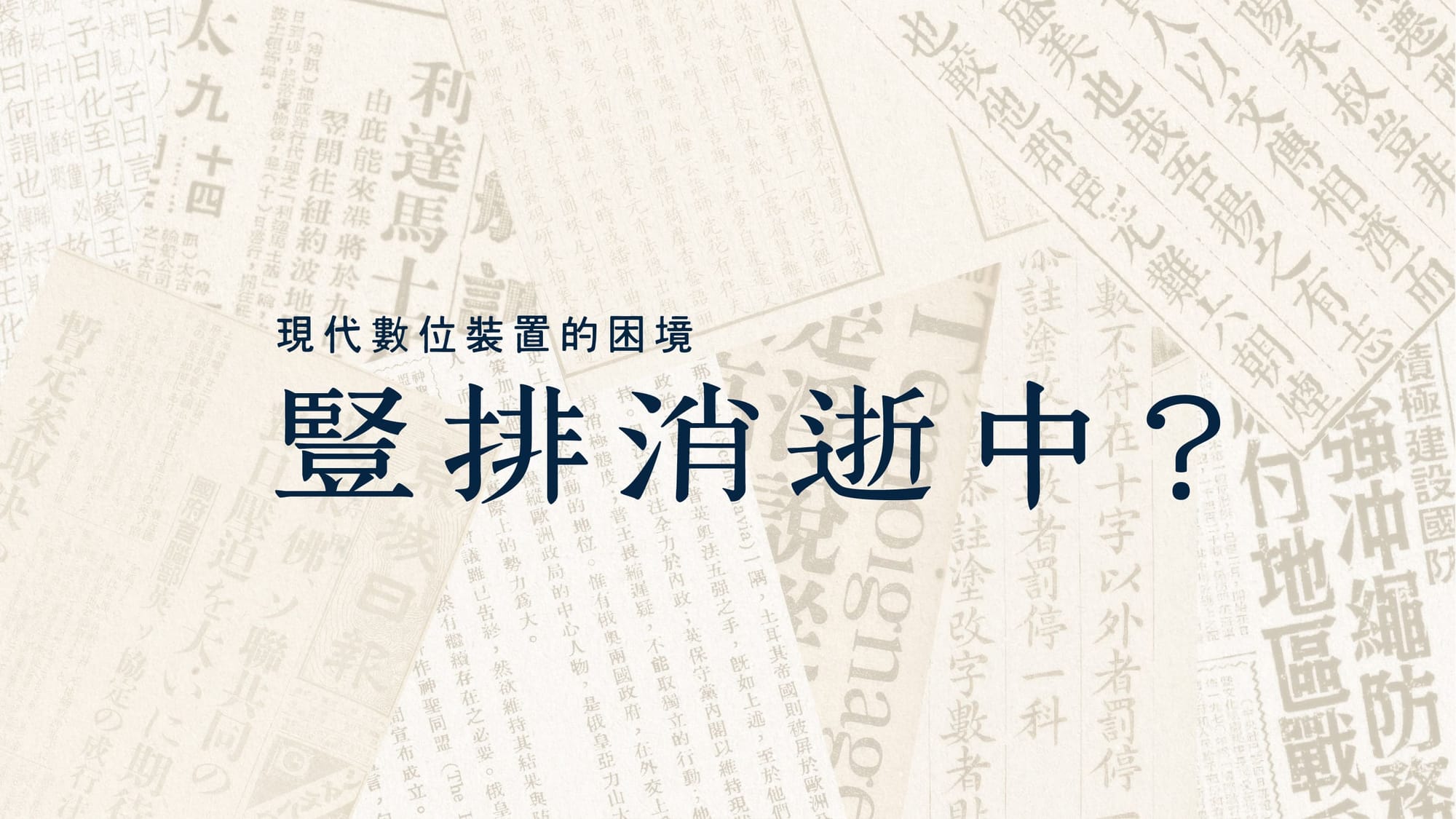
豎排消失中?現代數位裝置的困境
傳統的漢字書寫方向一直以來大多採用垂直形式。從以前的書法、刻本,再到現代的照排、鉛字,都多以這種形式與大家見面。
豎排/縱書
傳統的漢字書寫方向一直以來大多採用垂直形式。從以前的書法、刻本,再到現代的照排、鉛字,都多以這種形式與大家見面!
不過,這一切在進入數位時代後,開始發生變化,豎排開始漸漸消失,取而代之的是橫排文字,從電子文書到社群軟體絕大多,皆已改為橫式。
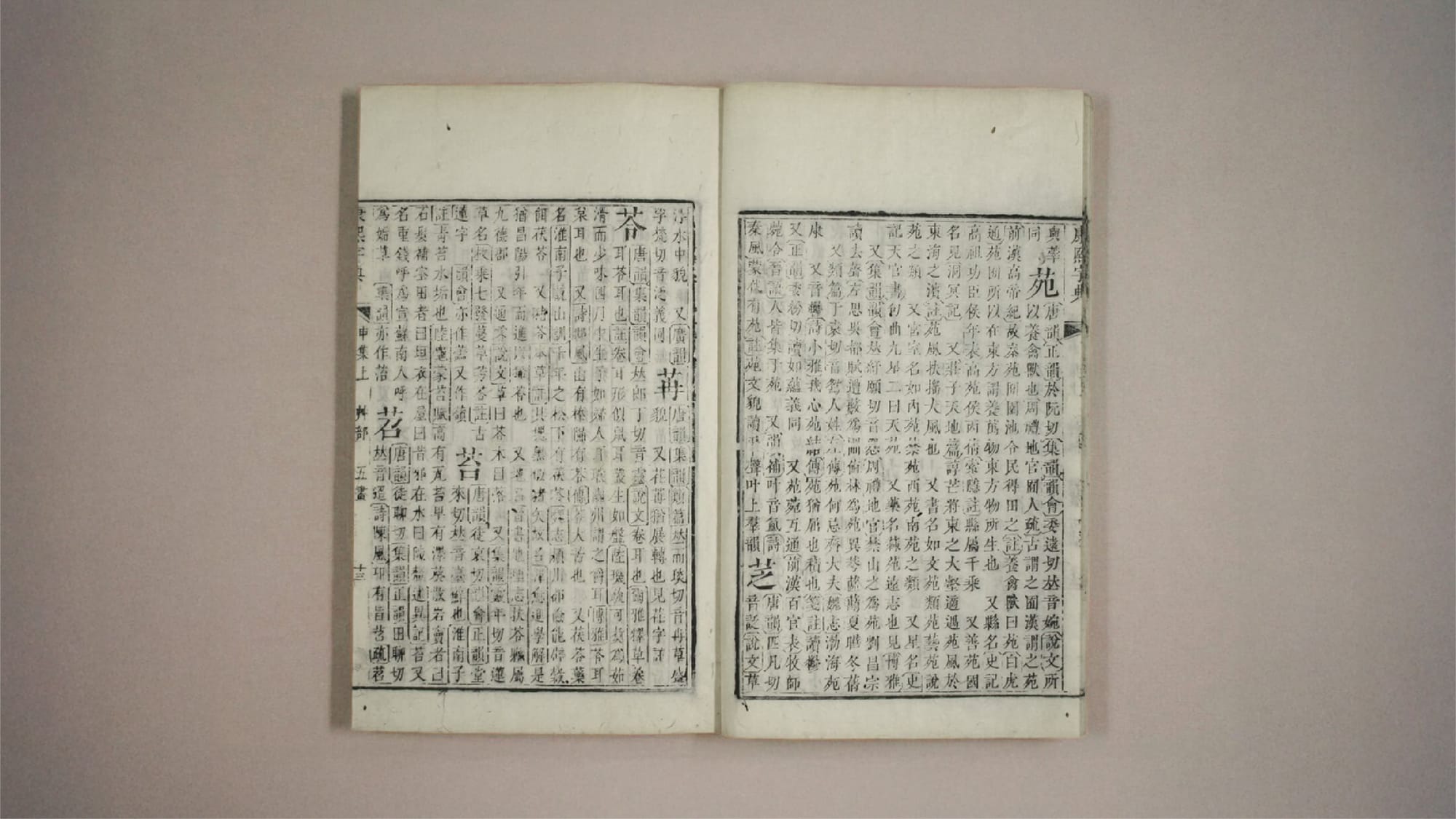
來自技術的侷限。
這一切的濫觴要從1973說起,當時美國Xerox公司,推出了Xerox Alto,這是世界上最早成熟的圖形化作業系統(是的,最早的GUI操作系統不是Microsoft、IBM或Apple推出的)。
再往前推的貝爾實驗、AT&T,甚至回朔到艾倫·圖靈......等人,這些公司、研究者絕大多數都來自歐美,或在歐美國家進行開發,所以他們用自己熟悉的語言開發在合理不過。
從技術層面來說,英文的組成也比中文等語系少得多,透過少數的字母符號組合不同結果,這在當時記憶體珍貴的硬體條件下,是最經濟的考量。
基於這樣的原因,自然的就會以拉丁為優先,或具體來說,是優先支援ASCII編碼的文字、習慣,而這些文種的書寫系統本生就是以橫排為主的。造就了現在以橫排
也沒這麼絕望?
講到電子裝置上的豎排,其實「電子書」就是最佳案例,目前主流的電子書裝置,大多可支援豎排模式。不是說逐漸消失嗎?
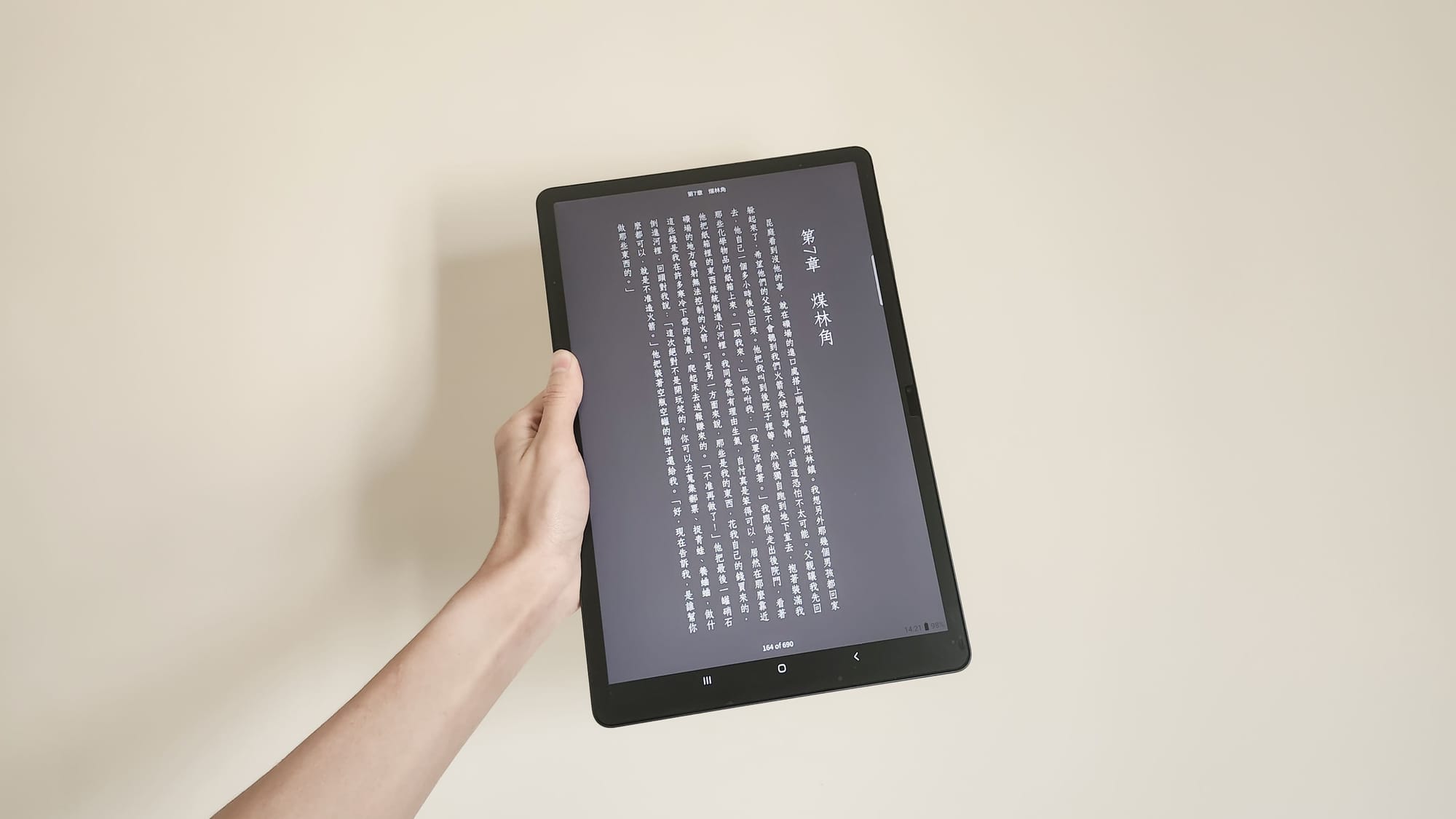
要回答這問題,要先掉書袋一下,如果你是電子書讀者,可能聽過電子書是使用 epub 格式,這種格式其實底層就是網頁技術,基於HTML 與 CSS,再加入配置文件等封裝成以.zip為編碼的文件。
既然是基於HTML 與 CSS,那當然是用瀏覽器解析囉!大多數的電子書軟體在你閱讀文章時,都會透過內嵌的小瀏覽器(通常是以Chromium為主,因為原生移動端Webview可能存在CSS兼容、效能等問題),進行解析。
沒錯!瀏覽器是支援的!這最早是在大約在2010年底時,由日本的專家學者提出相關草案,後被負責維護CSS的W3C組織正式支援。(這之中要感謝W3C團隊與特邀專家,這是個長故事,未來有機會也能在分享)。
瀏覽器是種選擇,但不是唯一。
只有瀏覽器支援豎排遠遠不夠。因為WebAPI的崛起,瀏覽器愈發強大,不僅可以編輯文件、剪輯排版,甚至是建模。即便如此,許多時候軟體還是需要深度與硬體、系統交互,我們不會所有的軟體都基於瀏覽自開發, 因為存在安全、效能以及使用者體驗之問題。
就像是instagram即便網頁版功能十分強大,但手機端應用依然採用React Nnative開發(編譯後元素元件會變編譯成平台原生)這樣可以有更棒的用戶體驗,以及一些需要與操作手勢相關的行為。
所以,瀏覽器並非所有,即便將它包成APP或是PWA,也無法避免一些缺點。例如:銀行APP需要安全隔離。
又或是你今天打算做一款離線使用的記帳APP(大Vibe Coding時代,大家不知道為何都喜歡做這個),想使用資料庫保存資料,如果使用基於瀏覽器的PWA技術,那選擇可能剩下不多,最常見是使用 indexedDB,以類似Json形式存入,但這樣不僅有容量問題,如果備系統清除快取,可能資料就不復存在,不力資料持久化,退一萬步使用SQLite WASM還是有穩定性問題。這再次證明,框架或原生應用必須存在的現實。
除了瀏覽器以外的選擇
剛才舉證了瀏覽器並不能取代所有APP。接下來要談談還有甚麼做法。最好理解的就是原生平台iOS用SwiftUI,Android用Jetpack Compose,這是最直接的方法。
當然所謂的跨平台框架,也十分盛行,最有名的非React Nnative莫屬,由Meta團隊開源(請注意此處提及的是React Nnative非React!)。以及後起之秀Flutter,這是由Google維護超級具有野心的框架,目前可以編譯成iOS、Android、Windows、Web端。
講了這麼多,困境在哪?
困境在於除了瀏覽器外,其他框架、平台,無一支援垂直排版。是的,很遺憾無一支援。
豎排/縱書難在哪?
聽起來只是將文字方塊換方向排列,但事實上CJKV排印充滿著玄機,舉凡:避頭尾、日文假名、諺文、標點擠壓,還有地區差異,以及多文種混排的問題。光是母語用戶,要將這些規則描述成規格文件,就要花上許多時間,更別提大多來自非CJKV母語者的開發團隊要將規則轉換程式碼實踐。
W3C不是成功了嗎?其他團隊不跟進?可能沒這麼樂觀!瀏覽器最早就是為數位文字顯示而生,看看HTML的全名就知道「HyperText Markup Language」。所以開發小組有深厚的相關經驗與願景。
然而其他框架、SDK初衷並非如此,他們還必須要關注、編譯、效能、硬體橋接、大大小小兼容性的問題。在Flutter中有人提交了相關問題,而Flutter團隊則回應了,在一開始就並不打算支援該功能。
沒有替代方案?
可能有人會想說使用圖片、PDF形式,但這樣治標不治本,首先這樣鑲嵌的文件無法做到響應式,也無法動態更新,容量、效能也不盡然理想。
也許......我們能做點什麼?
TwinType身為文字的使用者,中文字的使用者,漢字的使用者;身為設計者,字體的設計者,程式的設計者。我們或許能做點甚麼;我們或許要做點甚麼?
既然沒有輪子,那就造一個,我們決來編寫開源套件,解決該問題。我們決定先以Flutter為試驗,開發一個套件處理CJKV中文排版的套件。
會選擇Flutter的原因?根據Appfigures統計數據,Flutter在兩大移動端中都是僅次原生框架的開發套件,同時也是TwinType常用的技術棧,有較多調試經驗,故選用。
隆重介紹Bambook:Flutter豎排版套件
這是一款針對 Flutter 的套件。可你提供您垂直排版能力,為 CJK 語種提供另一種選項(甚至在蒙古文中是唯一選項)。該文字排版引擎,支援垂直書寫、縱中橫、避頭尾與標點視覺修正等功能。
目前版本為0.0.4(2026.02.01),我們將持續擴充功能包括,更好的支援蒙文、注音以及標擠壓、OpenType等特性。期待看到以豎排/縱書設計的UI應用遍地開花。